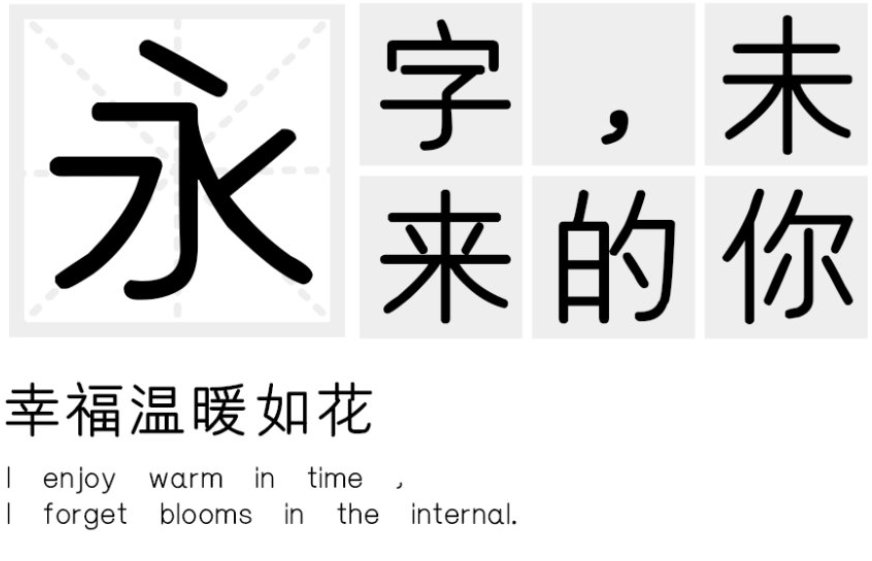
汉标中圆体发布
字体名称:汉标中圆体
字体类别: 圆体 黑体
适用场景:广告、包装、品牌形象
汉标中圆体简介:汉标中圆体是一款弧度非常优美的中文圆体字体,笔画纤柔饱满,结构舒展,字形圆润饱满,用笔简洁,有满满的可爱小女生的气息。适用于文艺类的书刊、品牌广告和产品包装设计,以及社交网络的个性化用字。
汉标中圆体预览图展示: